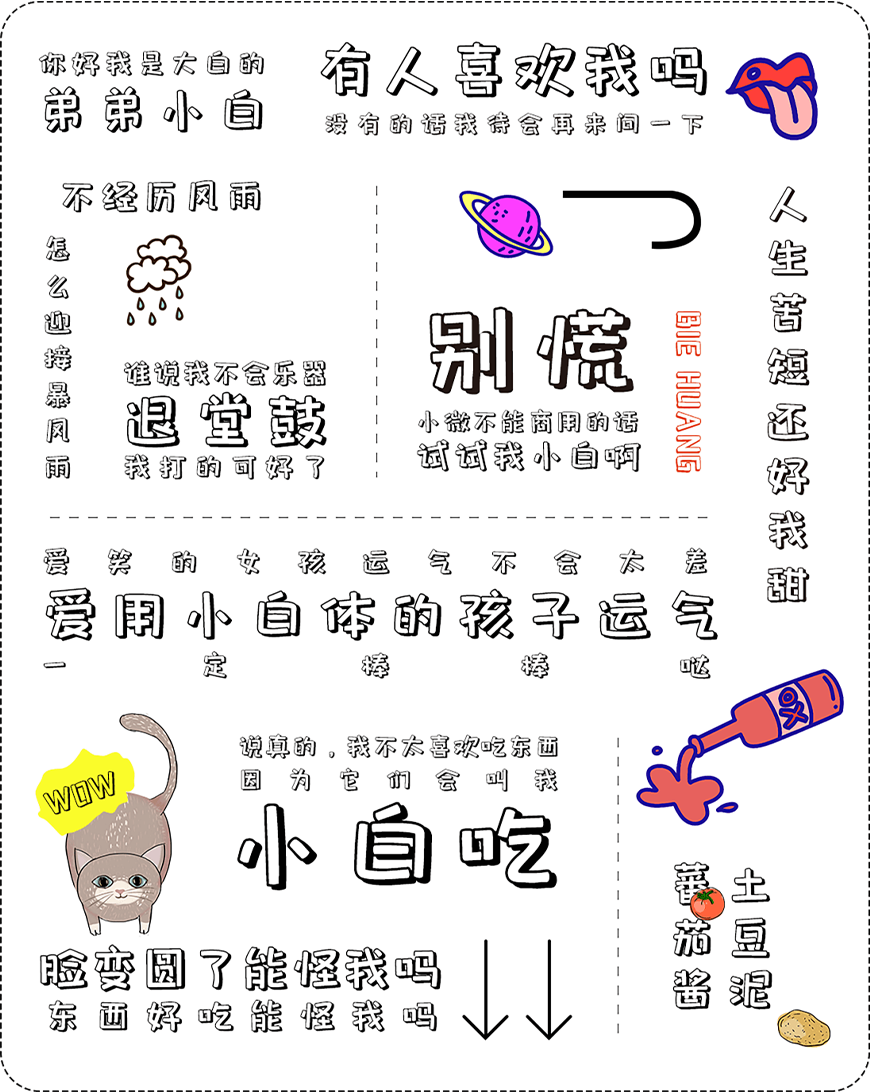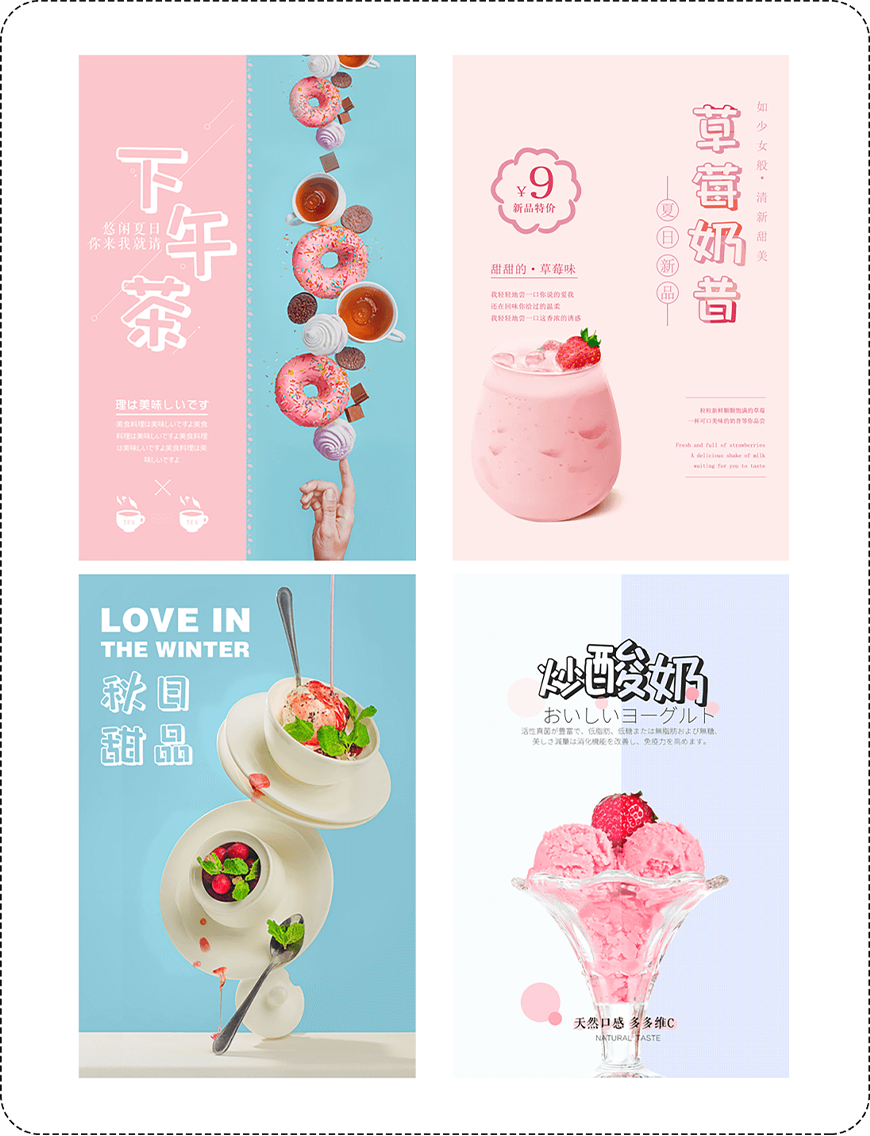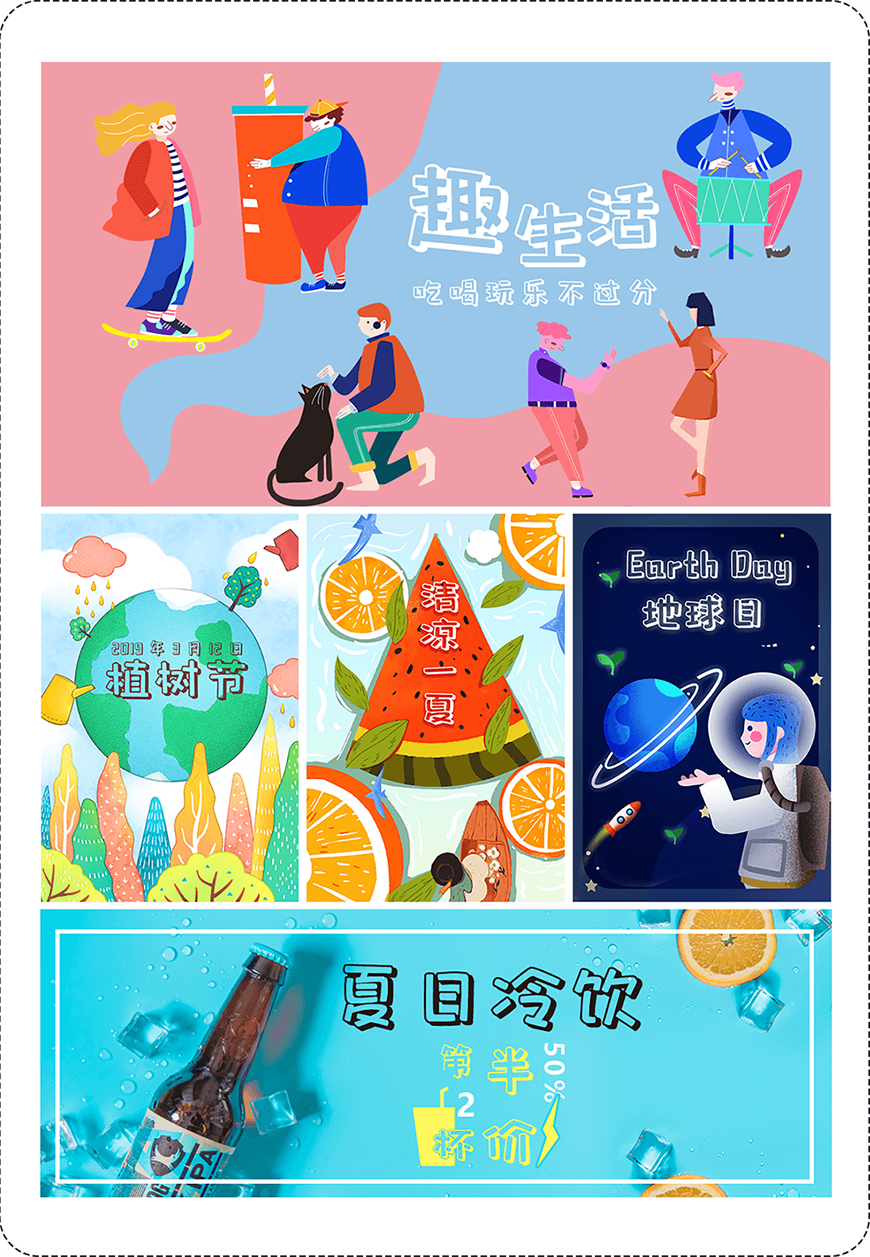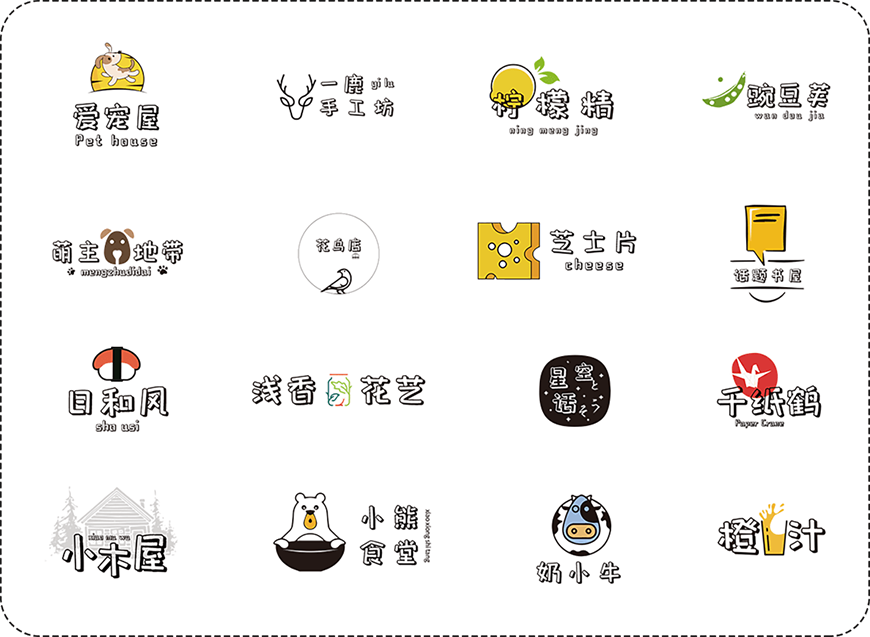
包图小白体
包图小白体是一款简单而可爱的创意字体,以其独特的风格和设计成为了平面设计中的热门选择。在字形笔画上,包图小白体独具匠心地弱化了折笔的弧形,采用了平直的笔画,竖弯钩则被转化为了竖折,同时更加简洁的钩笔画也省去了许多笔画末尾的小尾巴,使得字体更加直白可爱。
包图小白体的笔画粗短,形状如同柯基的小短腿,这使得字体显得更加可爱。与细长的字体相比,包图小白体更加轻松活泼,给人一种亲切感。整体形态采用了镂空的制作技巧,这不仅增加了字体的立体感,也让字体更加醒目。
包图小白体适用于多种场景,包括品牌标志、海报、包装、影视综艺、游戏、漫画等。无论是在哪种场合下使用,包图小白体都能够成为人们所钟爱的设计元素。此外,这款字体还采用了GB2312编码,共收容了7707个字符,包括6763个简体汉字、110个大写字母、139个小写字母、102个数字、95个标点符号以及其他特殊类符号和字母。